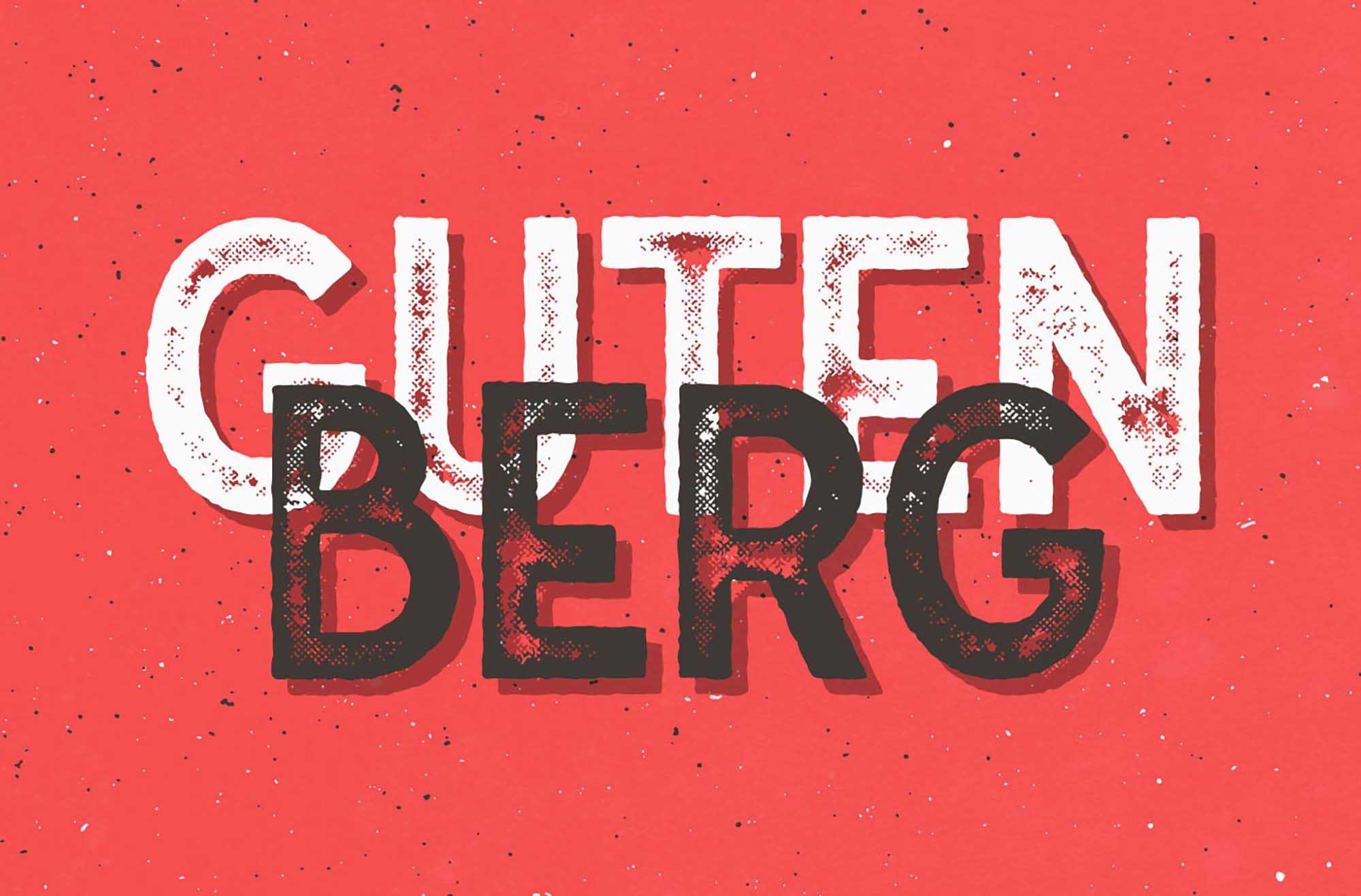
Descubra a magia do Gutenberg Font Family, uma família de fontes sans serif que vai transformar a aparência de seus projetos. Com linhas limpas e linhas suaves, essa fonte inovadora está disponível em formatos OTF e TTF, garantindo uma experiência visual incrível. Seja o clássico e elegante ou o estilo desafiador e grunge, o Gutenberg tem tudo o que você precisa para personalizar seu design. Seja para letras, números, símbolos ou até mesmo para os caracteres especiais, você terá uma vasta gama de opções. Além disso, a familia de fontes Gutenberg é multi-língue, garantindo suporte para qualquer necessidade. Não há mais motivo para preocupações sobre malfuncionamentos, porque o Gutenberg foi projetado para oferecer uma experiência de uso fluida e precisa, tornando a sua criação de materiais gráficos mais agradável e eficiente.